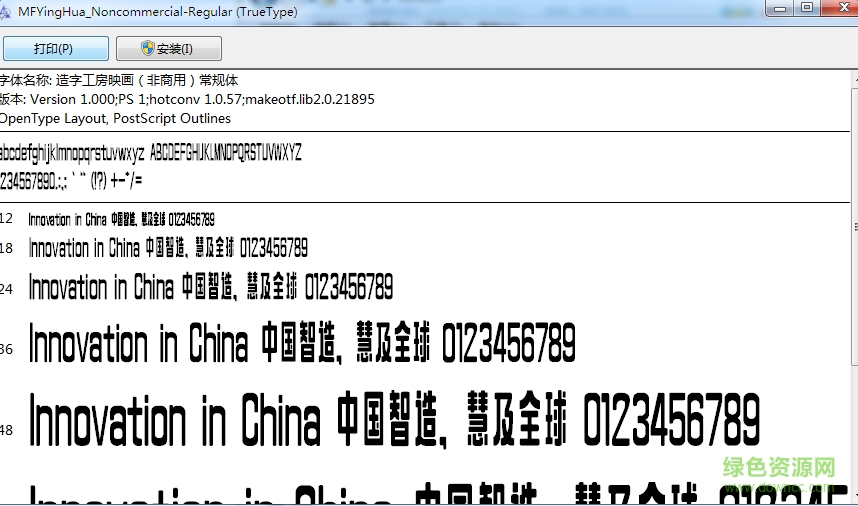
造字工房映畫體是一款詼諧有趣且又不失創(chuàng)新的一款全新字體,改編自民國時期的手繪廣告字形,適用于大標(biāo)題及個性品牌設(shè)計推廣等環(huán)境,有需要的朋友可以來綠色資源網(wǎng)下載!
造字工房映畫體源于民國時期手繪廣告字形,汲取民國字形橫粗豎細(xì)、重心偏高的特點,細(xì)長圓潤的筆畫讓字形更加個性十足,具有很強時代氣息,其形變幻靈動,結(jié)構(gòu)呼應(yīng)一致,字與字之間透露出婀娜窈窕之感,極其符合現(xiàn)代審美的多元化設(shè)計應(yīng)用的需求。